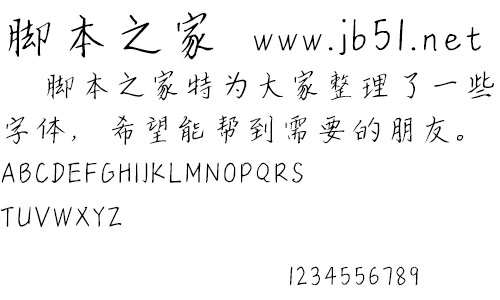
漢儀怦怦然心動(dòng)一款不錯(cuò)的藝術(shù)字體,由漢儀字庫出品,字體筆觸纖細(xì),書寫流暢,具有很好的視覺感,適合應(yīng)用于藝術(shù)設(shè)計(jì)、平面宣傳設(shè)計(jì)、網(wǎng)頁設(shè)計(jì),書法字帖等領(lǐng)域,需要的朋友可以前來本站下載。